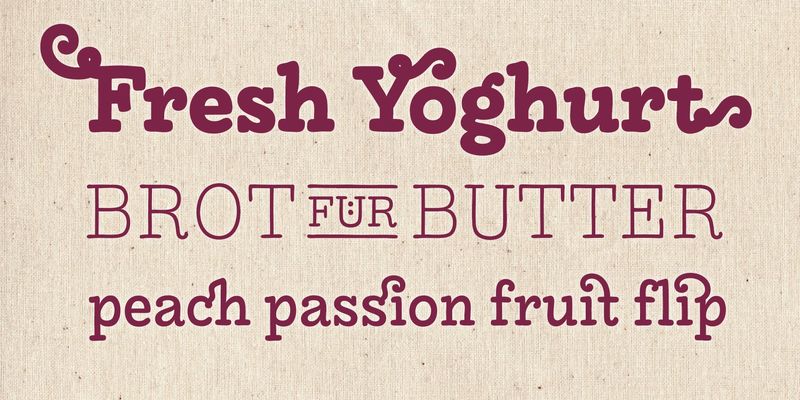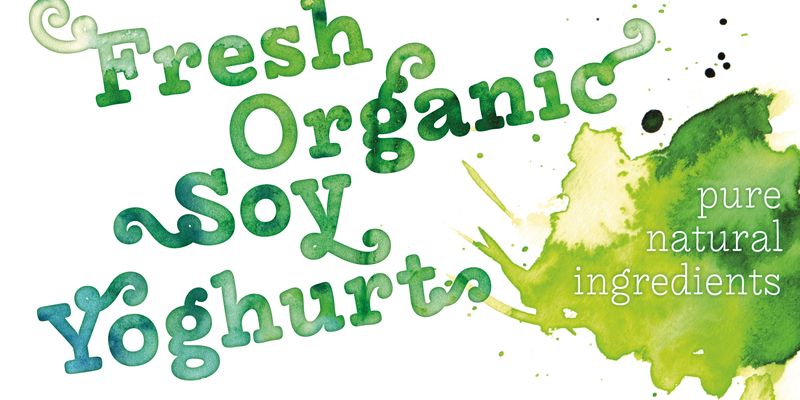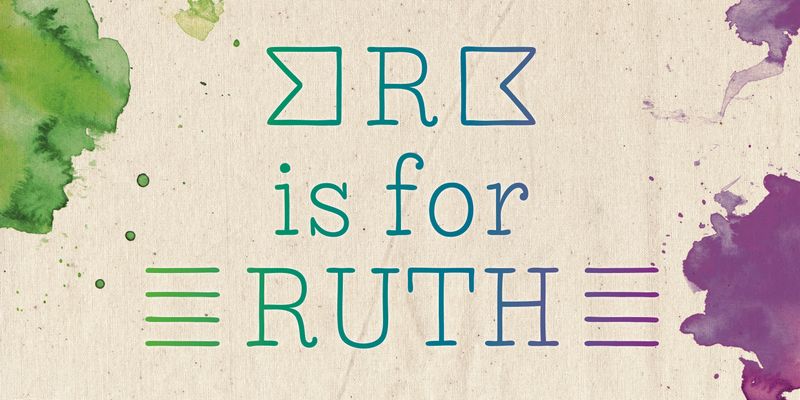
LiebeRuth ist Ihre 100 Prozent handgemachte Bio-Schrift. Sie liebt es, in großen und kleinen Formaten gesetzt zu werden, denn Lesbarkeit ist ihr zweiter Vorname. (Ja, wir wissen, dass das kein typischer Mädchenname ist.) Sie ist freundlich und höflich, aber sie hat auch ein paar Macken. Ihre Freunde sind beeindruckt, wie natürlich sie es schafft, jeden Tag auszusehen.
Ihre vier Schnitte sorgen dafür, dass Ruth für jeden Kontext die richtige Kühnheit hat: Geburtstagseinladung, persönliche Korrespondenz, Fotoalbum oder Plakatwerbung.
Während der Erstellung dieser Schrift aß ihre Designerin viele gesunde, biologische Lebensmittel. Wir glauben, das ist der Grund, warum Ruth so frisch und lebendig aussieht. Und natürlich wurde Ruth mit viel Liebe entworfen (was Deutsch für „Liebe“ ist – und sie spricht auch viele andere Sprachen).
Und noch etwas kann Ruth ganz wunderbar: Sie zeigt ihre kraus-gewirbelten alternativen Buchstabenformen, die über OpenType aktiviert werden können. Jeder Stil enthält mehr als 560 glutenfreie Glyphen – das ist ein tolles Angebot!